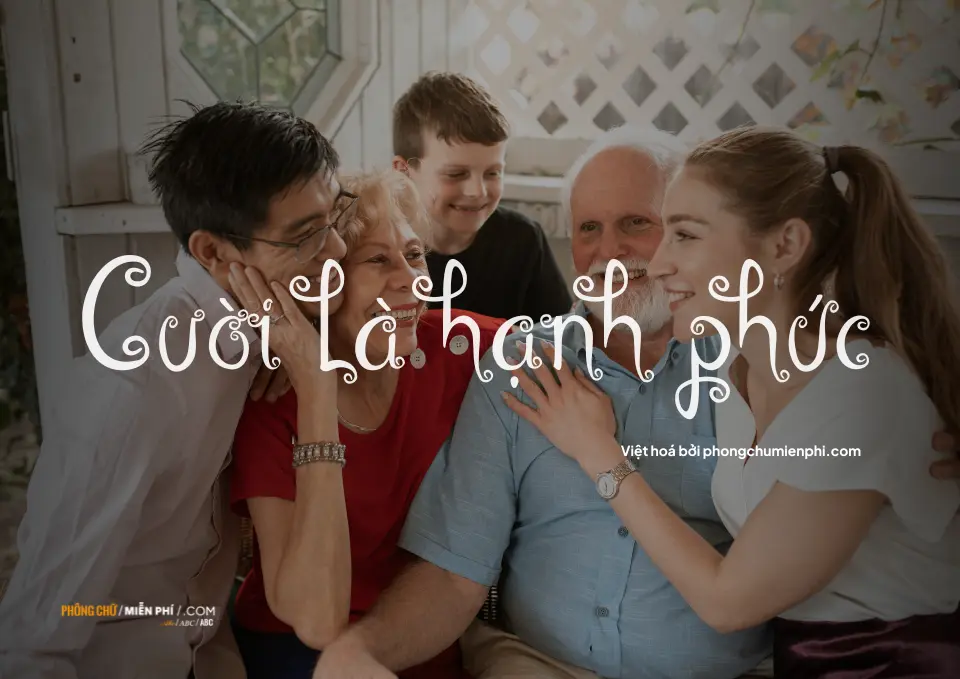
Tên font: Font Việt hoá AMSTERDAY SCRIPT
Font Việt hoá PCMP AMSTERDAY SCRIPT được việt hoá bởi phông chữ miễn phí.
Kiểu chữ Amsterdam có một đặc điểm riêng biệt, được thiết kế riêng biệt với đường kẻ trên cùng.
Phù hợp với nhu cầu của các dự án thiết kế. Có thể sử dụng cho nhiều mục đích khác nhau như tiêu đề, chữ ký, logo, thư từ, thiệp cưới, tiêu đề thư, biển báo, nhãn mác, bản tin, áp phích, huy hiệu, v.v.